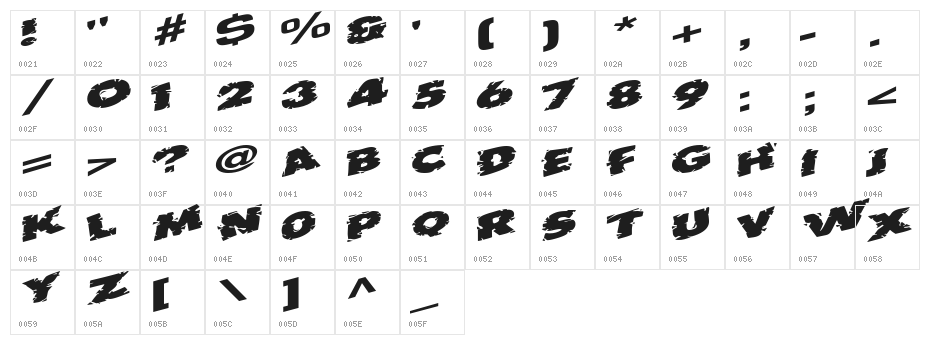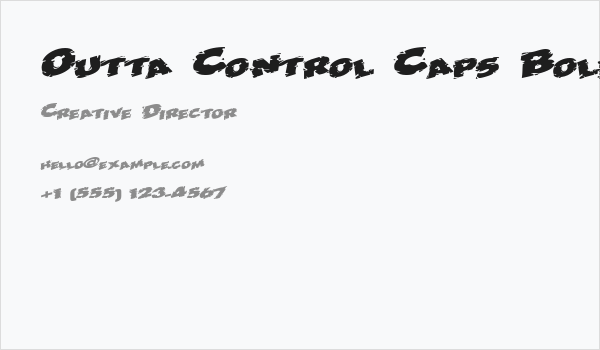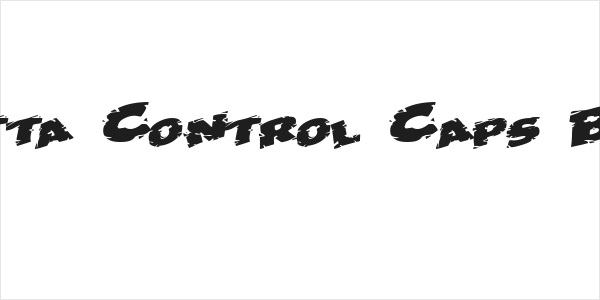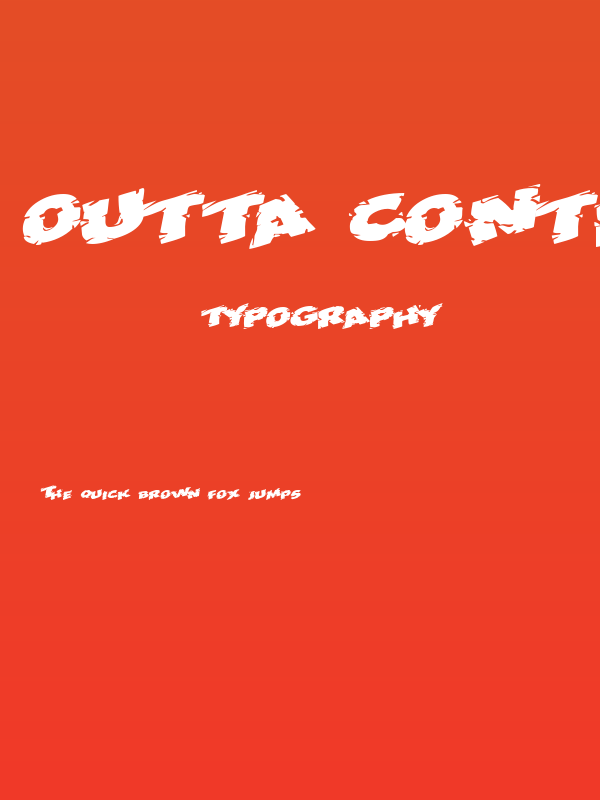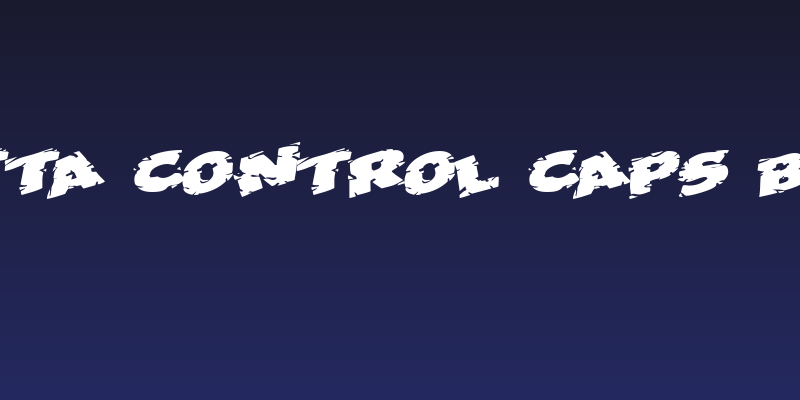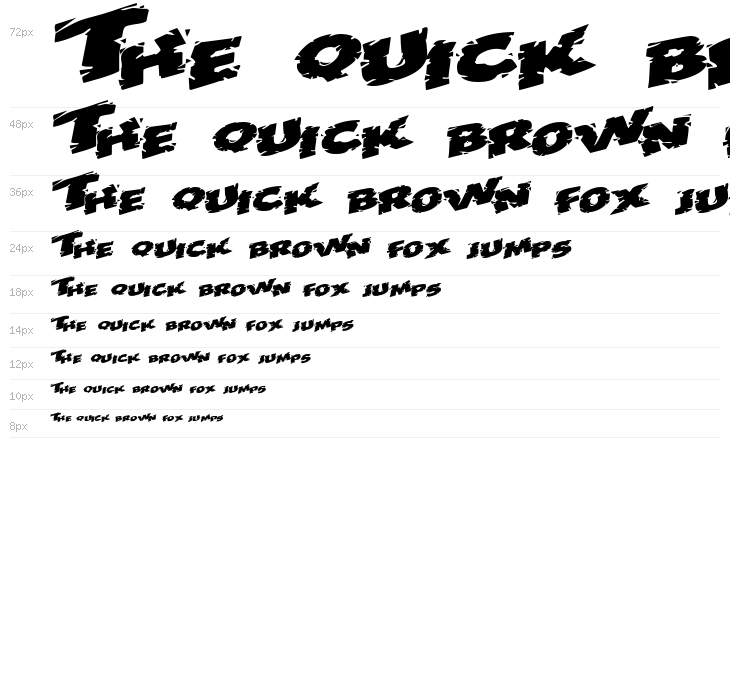
Outta Control Caps Bold Font
| Gesamtstil | Modern, Edgy |
| Vorgeschlagene Projekte | Ideal for music album covers, extreme sports branding, graffiti art, and edgy poster designs. |